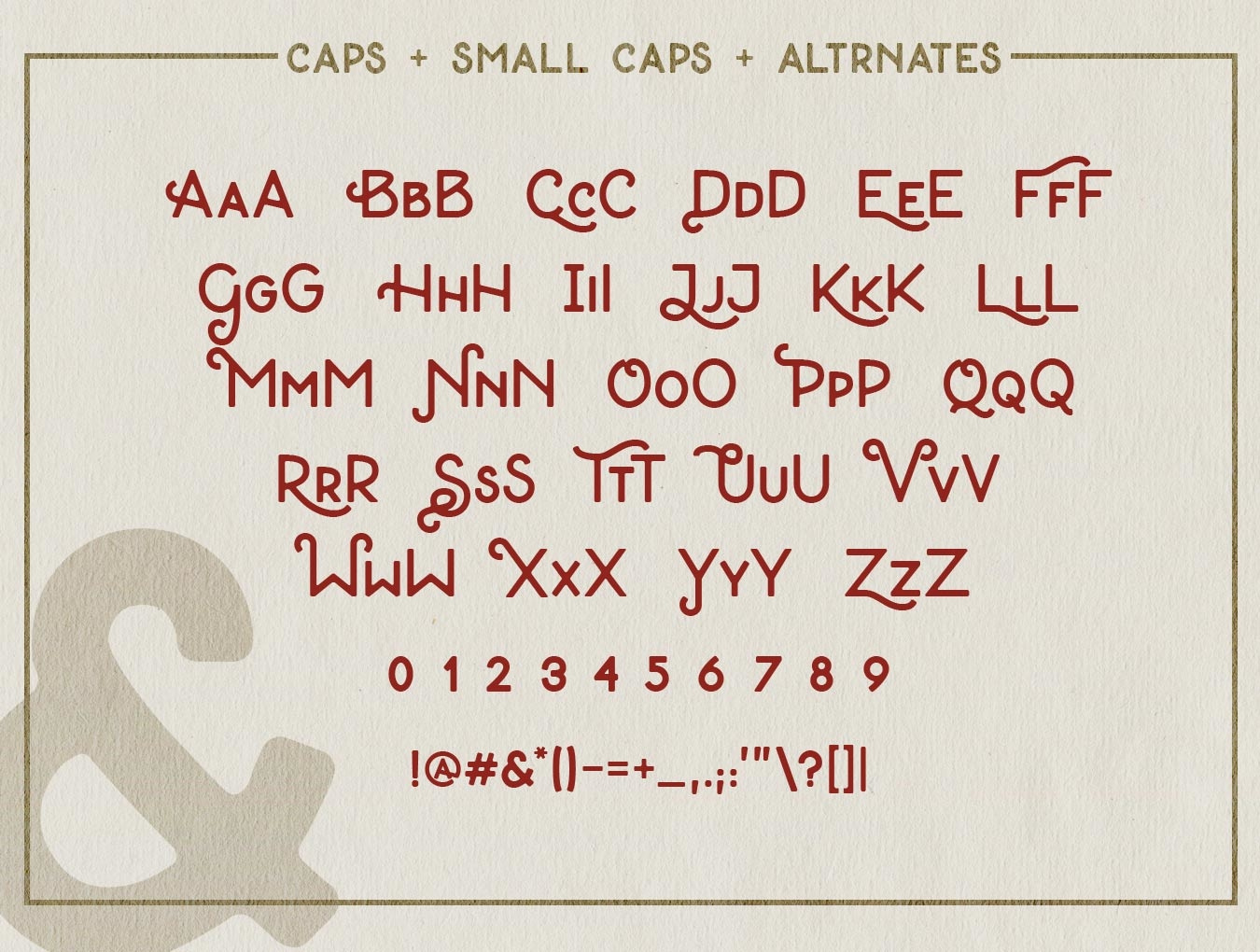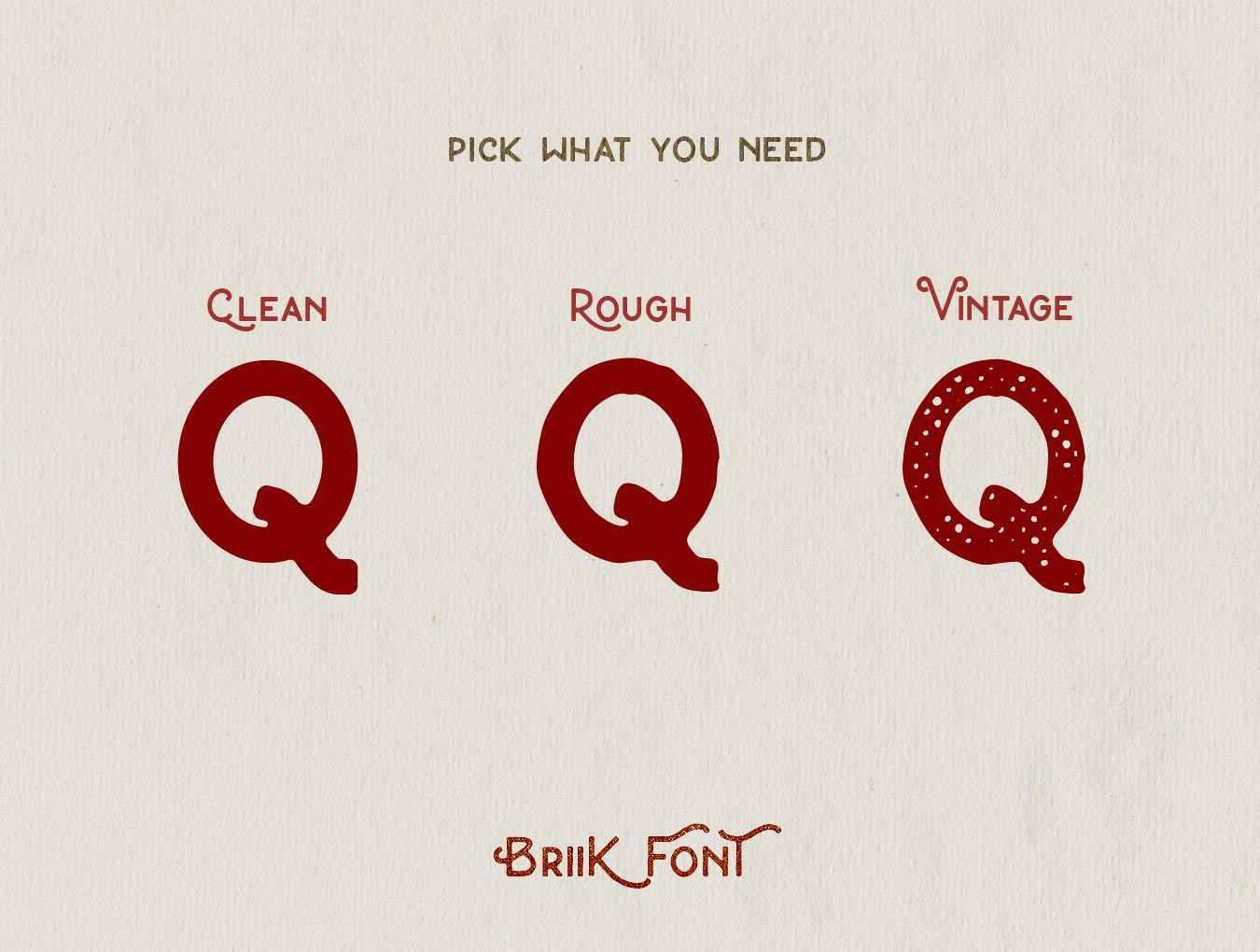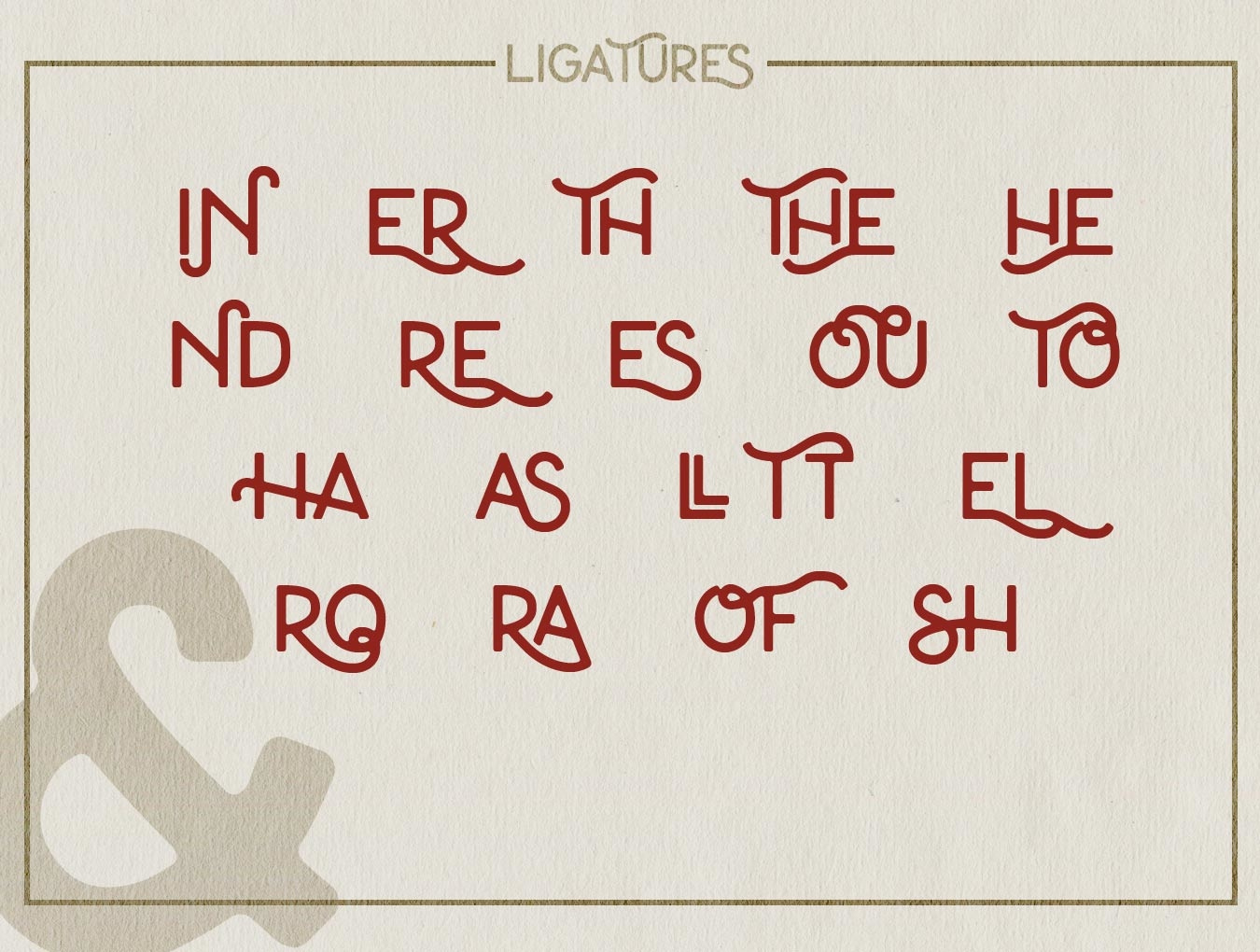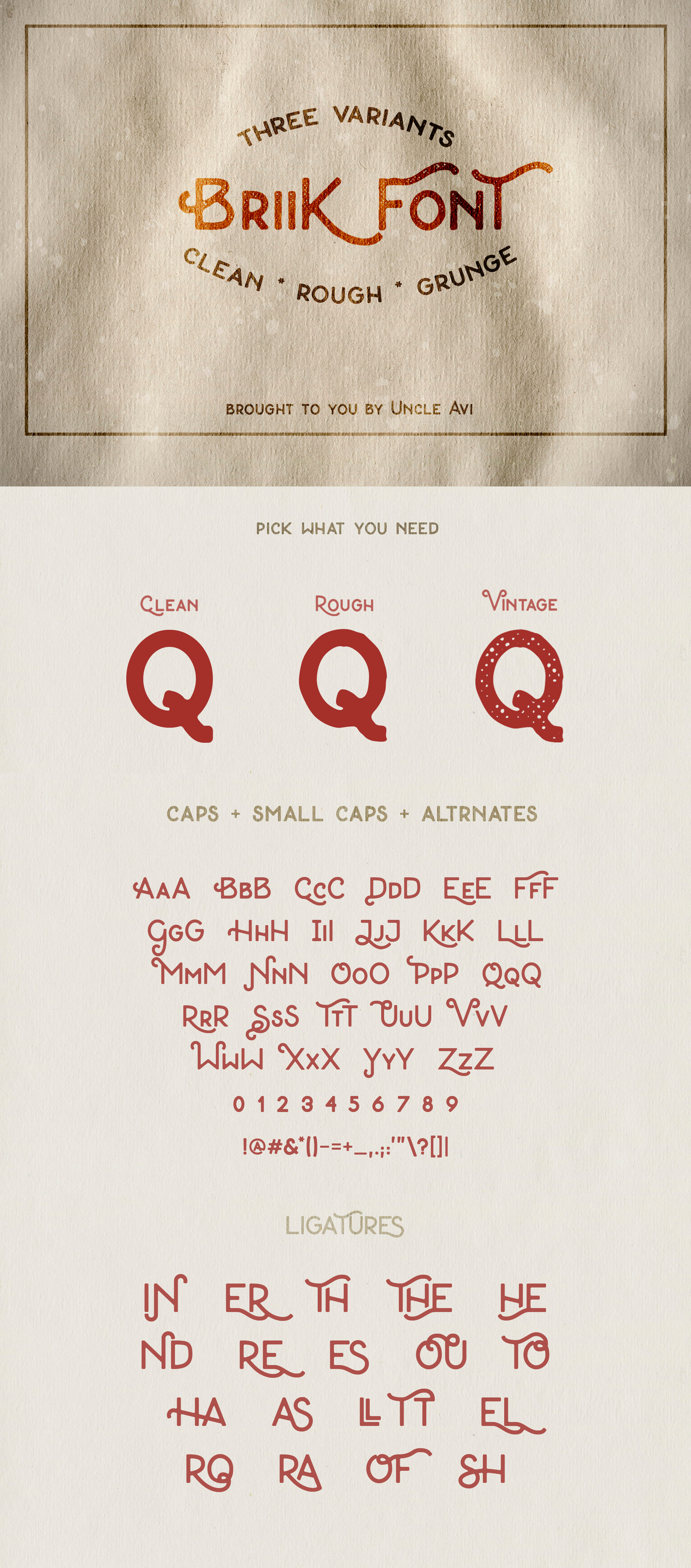
Briik不是太正式,也不是太疯狂的字体,Briik Hipster字体
Briik is not too formal and also not too crazy font, Briik Hipster Fonts
Briik不是太正式,也不是太疯狂的字体。这是标志和印刷工作的完美。它也与脚本和重的sans serif字体很好地配对。这是一个单重字体,包括3个变体:干净,粗糙和复古。 每个字母还有3种变体:小帽,正常帽和替代正常帽。此外,还有19个连字。 访问所有候选字形的指南:http://adobe.ly/1m1fn4Y如果您没有支持opentype特征的软件 - 不用担心 - 还有字体文件,它们会将字形替换为普通的帽形字形。